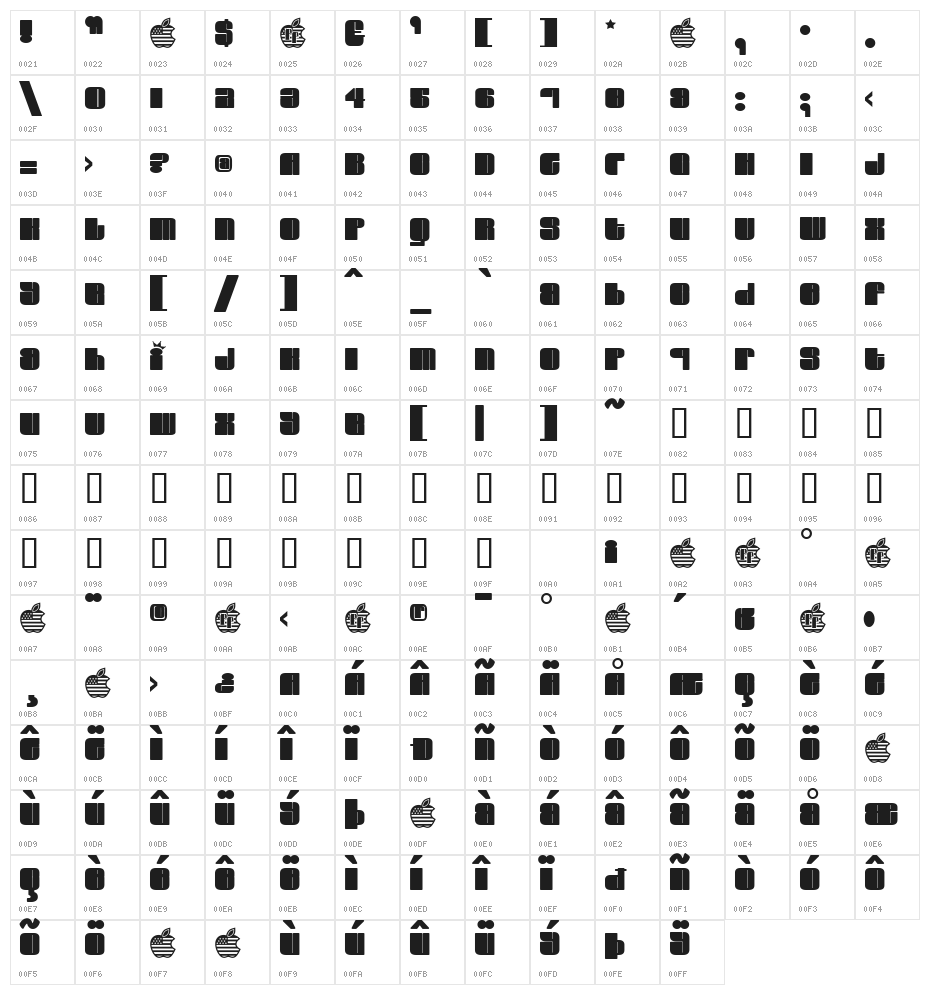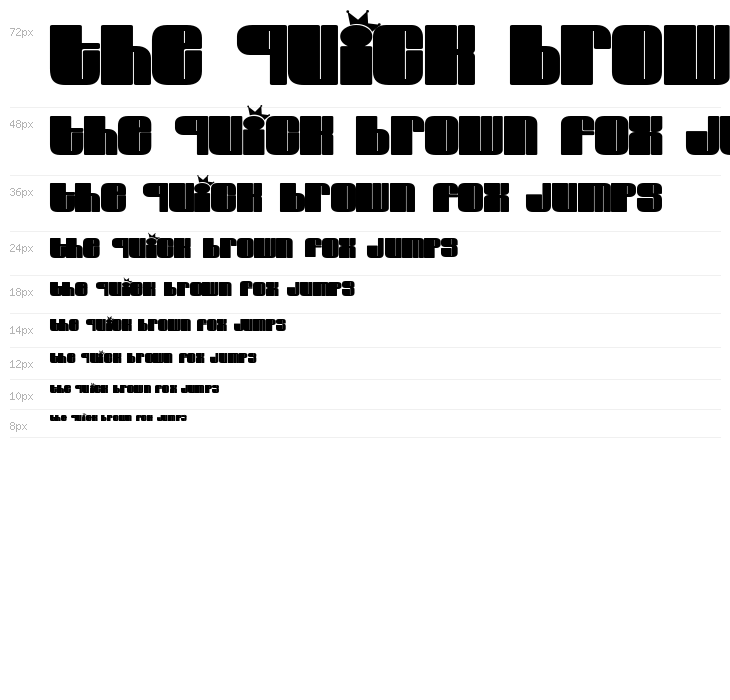
Elvis Font
✎ Decorative
| Vorgeschlagene Projekte | Ideal for branding, posters, album covers, and any project requiring a bold, standout typeface. |